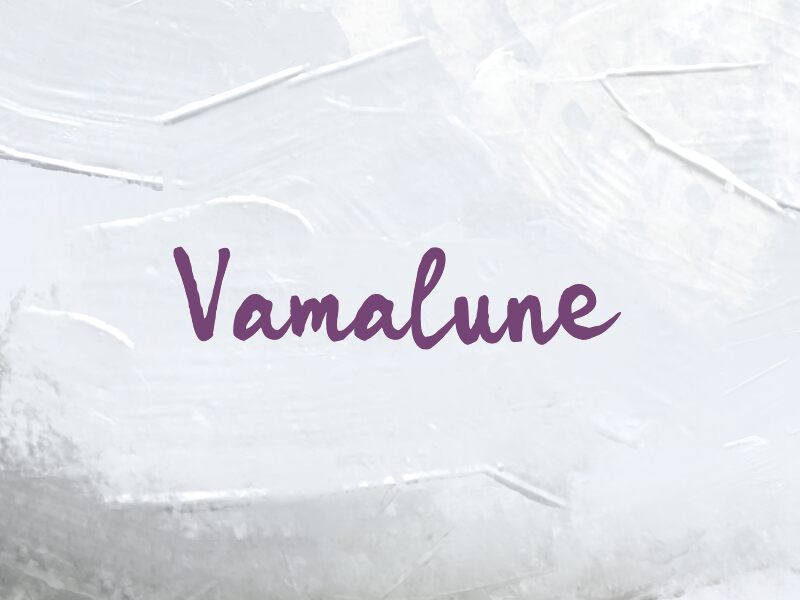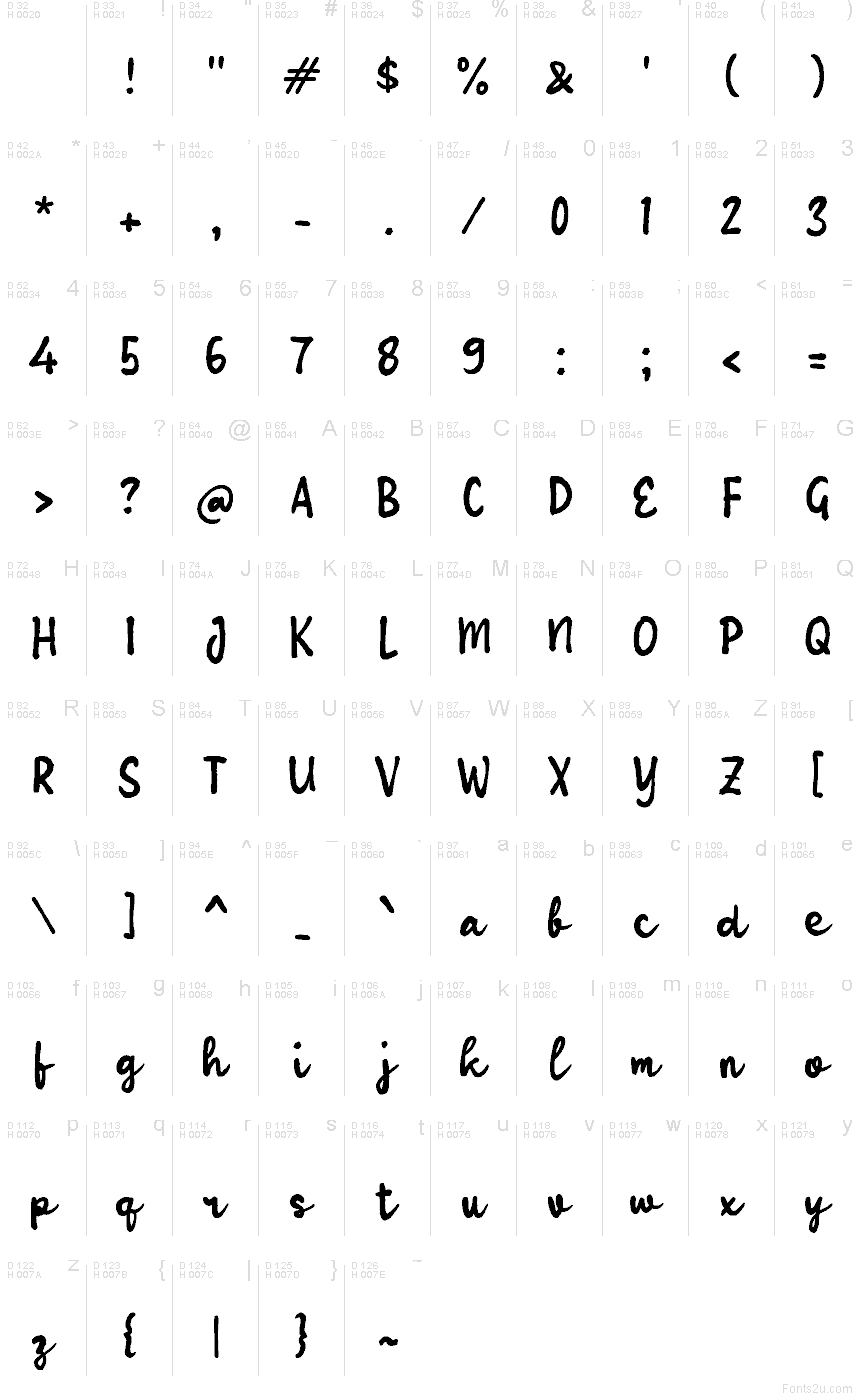
Vamalune Hill
Vamalune Hill od Wep je bezplatné ručně psané písmo, které definují široké tahy štětcem a volný, hravý rytmus. Písmena působí malovaným dojmem a míchají robustní oblé tvary s vysokými smyčkami, díky čemuž písmo působí ležérně a přirozeně.
Tento pohyb dává krátkým textům přirozené místo na menu v kavárnách, obalech, nadpisech pozvánek, přáních či příspěvcích na sociálních sítích. Skvěle se hodí také pro citáty v grafice nebo koncepty log, kde nepravidelná textura štětce a vzletné konce tahů dodávají hřejivý, rukodělný nádech bez nutnosti dalších dekorací.